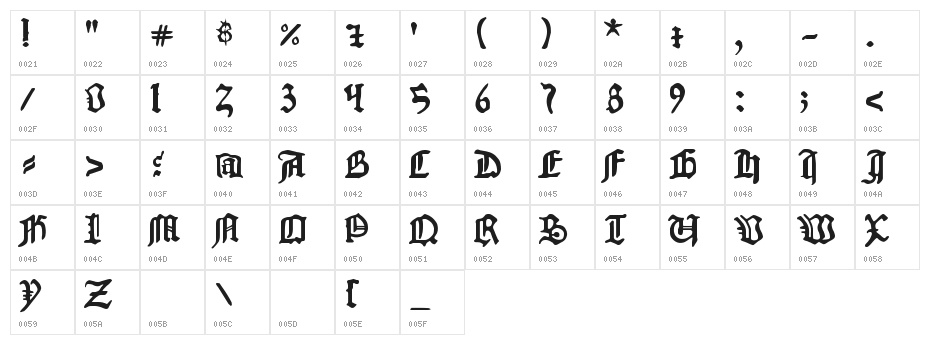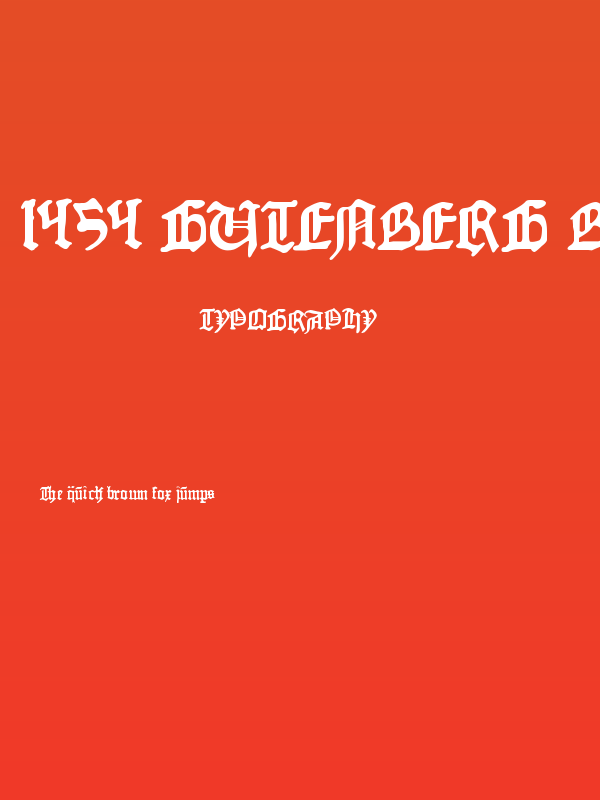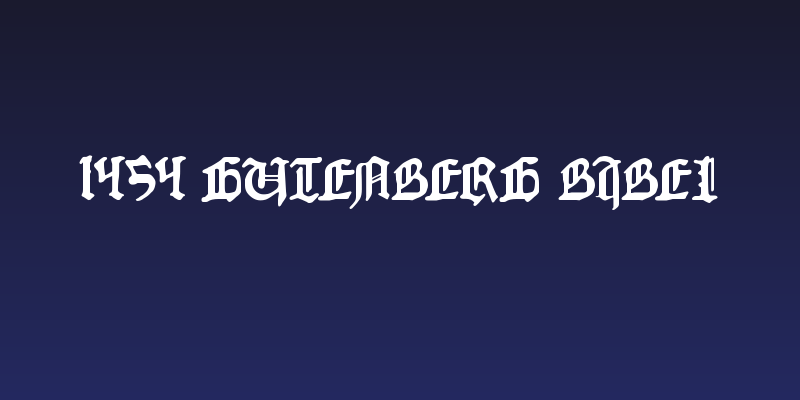
1454 Gutenberg Bibel Font
| Gesamtstil | Vintage |
| Vorgeschlagene Projekte | Ideal for historical documents, book covers, posters, or any design that requires a medieval or gothic aesthetic. |